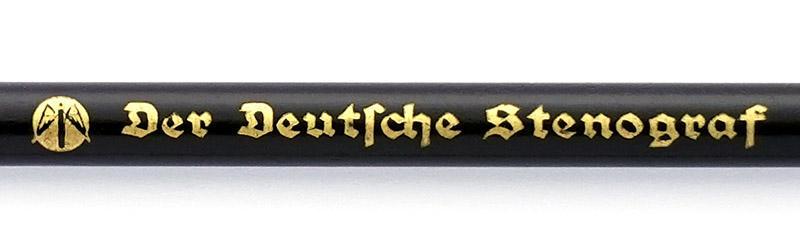
Suche gebrochene Schrift aus dem Prägedruck auf einem Bleistift
mein Exemplar des Bleistifts A.W. Faber 1400 № 2 (vermutlich 1920er oder 1930er Jahre) hat auf der Rückseite diesen Prägedruck:
Kann mir jemand sagen, welche gebrochene Schrift hier verwendet wurde? Ich suche den Schriftnamen zu Recherchezwecken.
Leider kenne ich nur das gezeigte auf dem Bleistift. Vielleicht gab es noch Gedrucktes von A.W. Faber dazu (oder einen Katalogeintrag), aber das weiß ich leider nicht.
Aber jetzt sehe ich es auch – es gibt z. B. beim „e“ leichte Abweichungen, aber vielleicht kann das ja auch am (Folien-)Prägedruck liegen.
Gibt es eine Schriftart, der dieser nahe kommt?
Suche mal nach der sgg. Bibelschrift, (1926-1928 by Bremer Presse). Die ist ziemlich nahe dran.